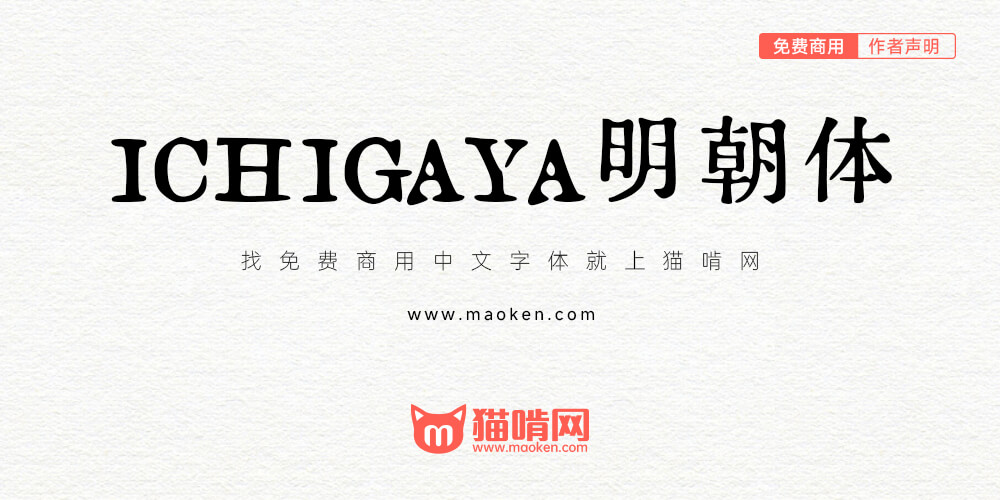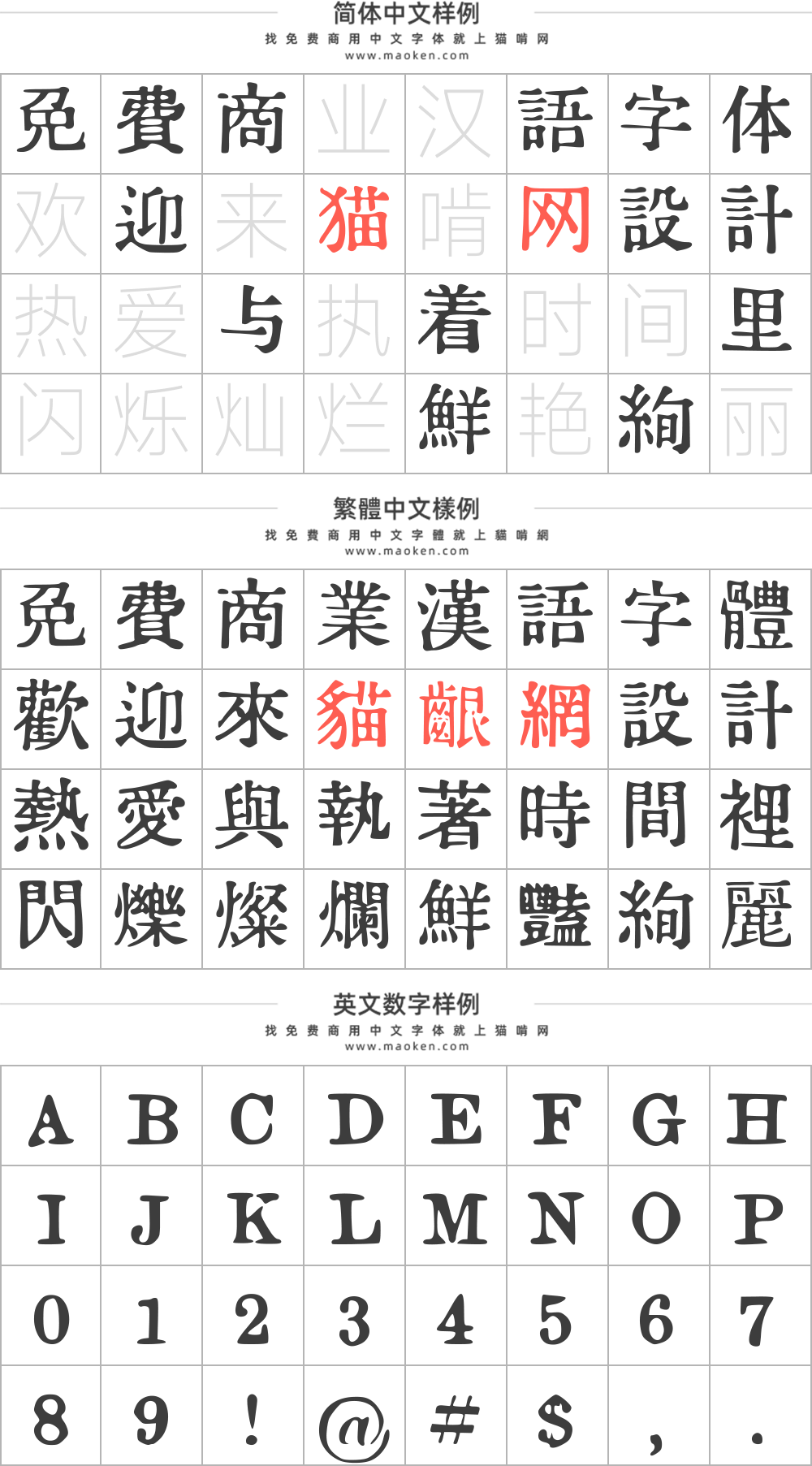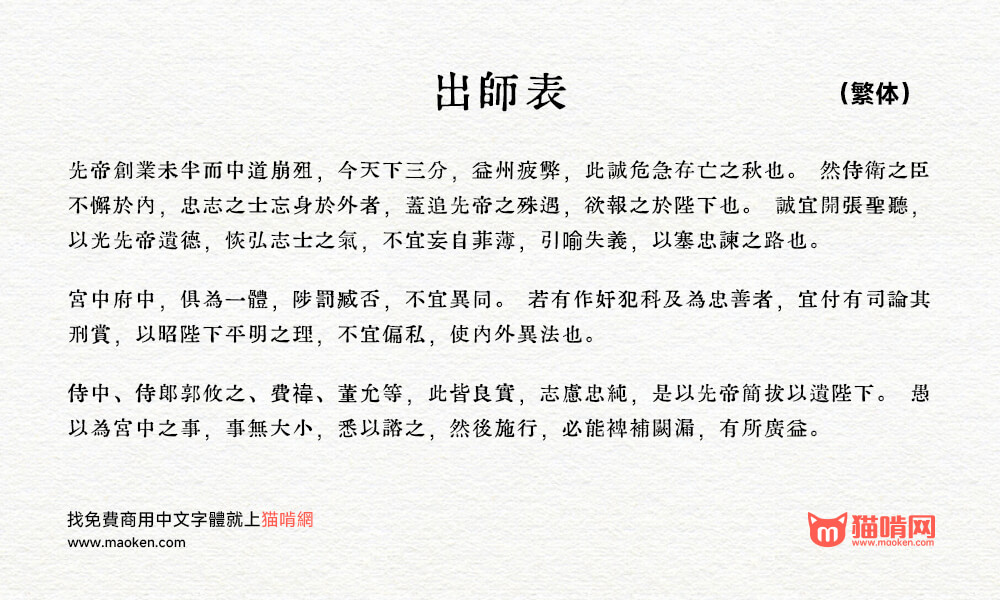
ICHIGAYA明朝体:基于大日本印刷有限公司的类型样本
字体作者:daredemotypo (日本) 字体字重:1个
ICHIGAYA明朝体是一款来自设计师daredemotypo的免费字体,使用InkScape的自动追踪功能将大日本印刷的前身企业秀英舍活版制造所的活字制作成字体。 大部分以市谷杜本和活字馆所有的《明朝五号活字摘要录》(1913年)为基础。
小遗憾,繁体不够,简体就更不够。
扫描得太糊完全不修的样子,尤其是“H”糊成“日”了,竖排特性没关联句号。